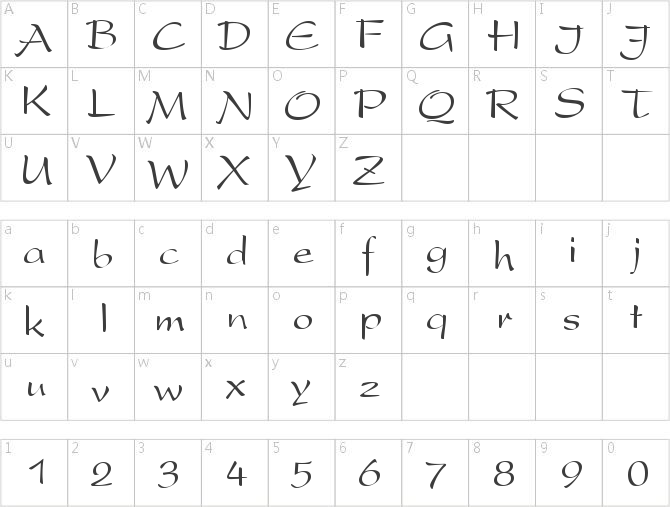
字體名稱: preston
prestonscriptregular
prestonscriptregular介紹
prestonscriptregular字體字庫是一款讓人賞心悅目、百看不厭的英文字體,適合各類廣告和產品包裝設計應用,字體大小0.04MB,格式為ttf字體,上傳用戶是鄒灣灣灣灣,作者/版權方為未知
prestonscriptregular效果圖